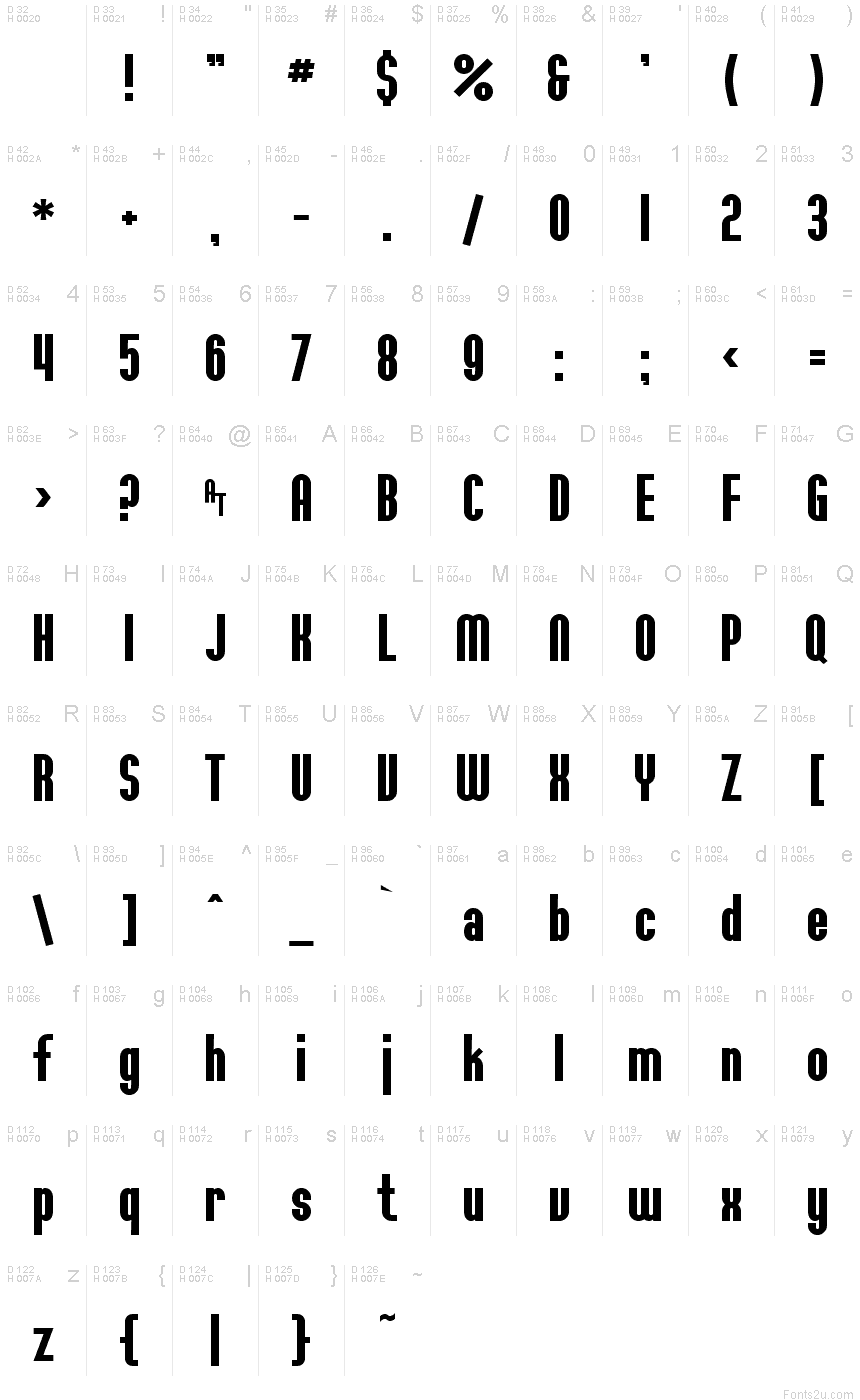
SF Willamette Bold، من ShyFoundry، هو خط مجاني مكثف بلا زوائد، يتميز بجرأة تشبه تصميمات الملصقات الكلاسيكية. الحروف طويلة ومتقاربة، مع أشكال مربعة تم تليين زواياها بما يكفي لكسر حدة التكرار الثقيل، مما يمنح الخط طابعاً حضرياً رشيقاً.
يتناسب بشكل طبيعي مع ملصقات الحفلات الموسيقية، وتصاميم ملابس الشارع، وعلامات الرياضة التجارية، وعناوين المجلات، والبطاقات التعريفية حيث تحتاج بضع كلمات إلى ترك أثر قوي. وباعتباره خطاً مجانياً مناسباً للعناوين المتراصة والشعارات القصيرة أو الأحرف الأوليّة، فهو فعال لأن عرضه الضيق يتيح لك تكبير الحجم دون فقدان ذلك الحضور المكتنز والقوي.